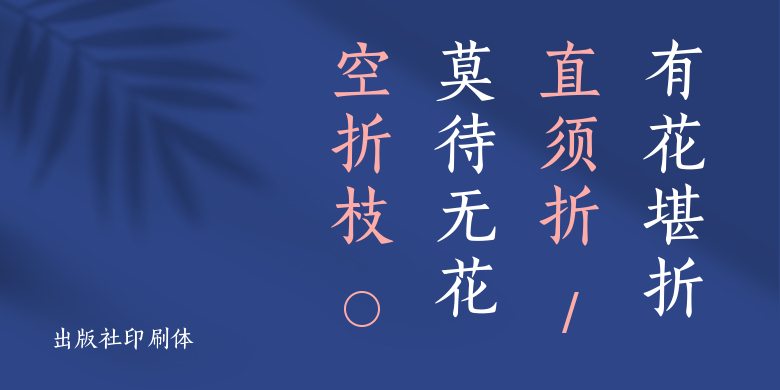
出版社印刷体
出版社印刷体,这款字体结构工整、笔画清晰,兼顾美观与易读性,适用于标题、正文、海报、包装、LOGO 等多种场景。字形优雅稳定,风格百搭耐看,适配日常排版与创意设计,让文字呈现更舒适、更具质感。出版社印刷体一笔一画,皆是细节,以均衡的比例、流畅的线条打造舒适视觉体验,字形端正大气,风格简约现代。无论是商业设计、品牌宣传还是日常排版,都能轻松驾驭,让文字更有格调与力量。出版社印刷体字体下载。